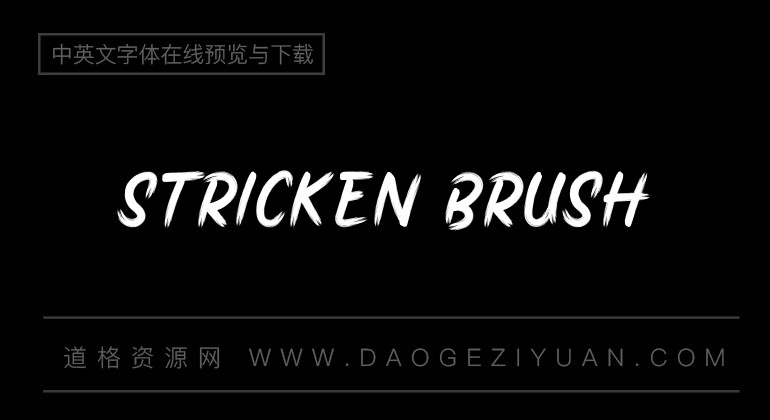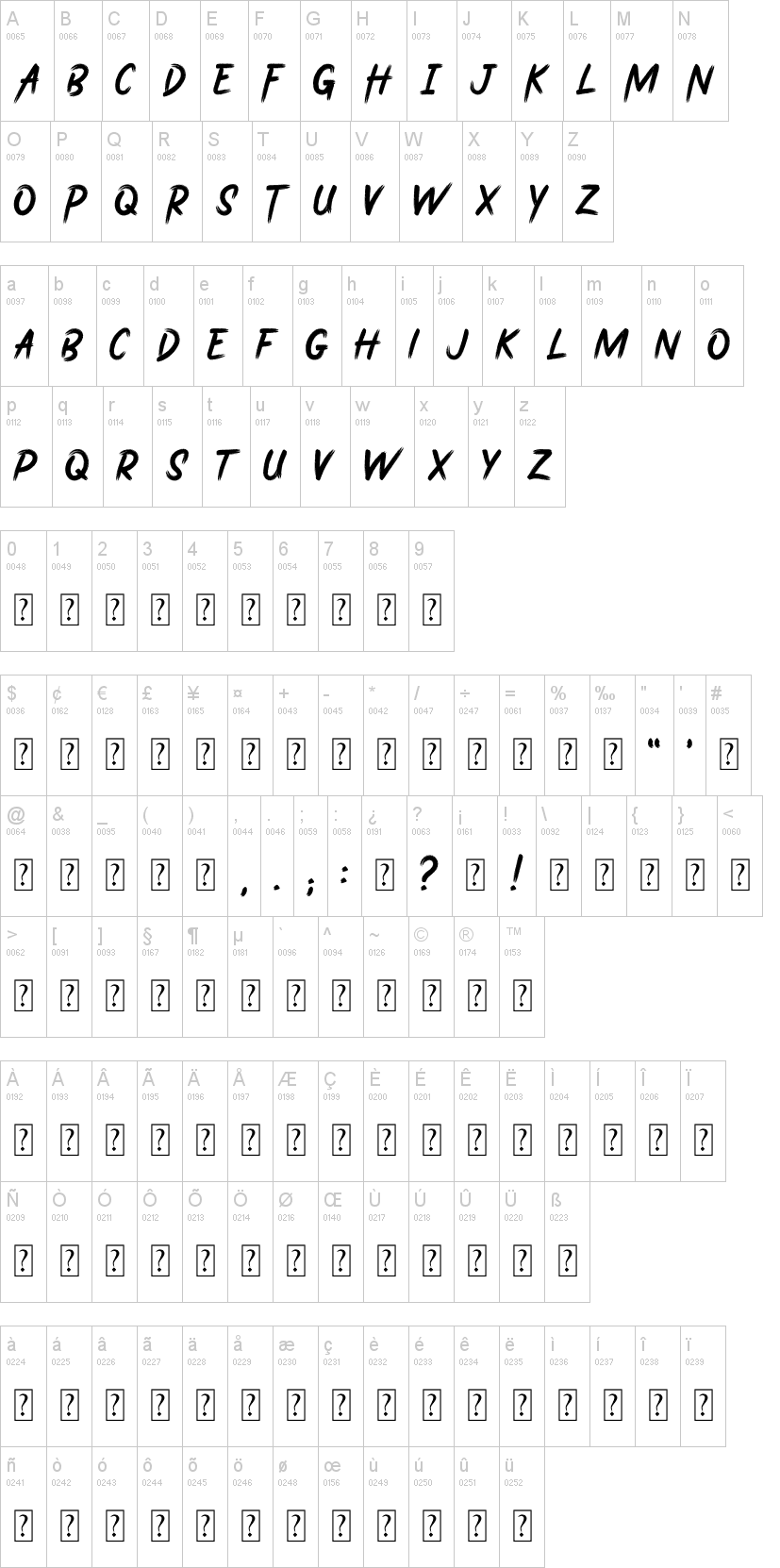
Stricken Brush
Stricken Brush 是一种手写风格的字体,由设计师 Gatis Vilaks 设计。它的特点是笔画粗细不均匀、线条粗细变化明显,呈现出一种狂野而自然的感觉。这种字体适用于多种情境,如海报、标题、标志或任何需要一种引人注目的字体的场合。 Stricken Brush 字体的可读性较高,因此它也可以用于正式文档中的标题或子标题。
Stricken Brush是一款非常不错的手写艺术字体,具有很好的视觉感,适合于文化类的宣传设计、商业类品牌的广告和产品包装设计以及个性化文字排版等较多场景。
Stricken Brush字符映射图